W dobrym składzie litery nie mogą walczyć o uwagę czytelnika. To właśnie drobna regulacja odstępów między nimi decyduje, czy nagłówek wygląda elegancko, czy po prostu rozjeżdża się wizualnie. W tym tekście wyjaśniam, na czym polega kerning, jak odróżnić go od innych ustawień składu i kiedy ręczna korekta naprawdę robi różnicę.
Najważniejsze rzeczy, które warto zapamiętać
- Regulacja odstępów działa na konkretnych parach znaków, a nie na całym akapicie.
- Największą różnicę widać w nagłówkach, logotypach i materiałach drukowanych.
- Nie myl tego zabiegu z trackingiem ani interlinią, bo każdy z tych parametrów wpływa na tekst inaczej.
- Najpierw oceniaj krój i rozmiar, dopiero potem poprawiaj szczegóły.
- W druku próbka testowa jest pewniejsza niż sam podgląd na ekranie.
Na czym polega regulacja odstępów między literami
W dobrze zaprojektowanym kroju pisma odstępy są wstępnie ustawione tak, żeby tekst wyglądał równo i naturalnie. Problem zaczyna się wtedy, gdy konkretne pary liter tworzą zbyt duże „dziury” albo zaczynają się wizualnie zlepiać. Właśnie wtedy kerning porządkuje problematyczne zestawienia i przywraca rytm całemu napisowi.
Najłatwiej zobaczyć to w parach typu AV, To, Ta, Wa, LT czy Yo. Same litery mogą być poprawne, ale ich sąsiedztwo zmienia odbiór. Dwie litery o skośnych kształtach, okrągłe znaki obok pionowych kresek albo duże wersaliki zestawione z małymi literami często wymagają korekty. Z mojego doświadczenia wynika, że to właśnie ten drobiazg najczęściej odróżnia skład „poprawny” od składu naprawdę dopracowanego.
W praktyce chodzi nie o matematyczną równość, tylko o wrażenie równowagi. Oko nie liczy milimetrów, tylko ocenia tempo i ciężar znaków. Jeśli napis zaczyna się rozbijać na przypadkowe kawałki, odbiorca czuje to od razu, nawet jeśli nie umie nazwać przyczyny. I właśnie dlatego temat odstępów jest w typografii tak ważny, szczególnie tam, gdzie tekst ma pracować na pierwszy kontakt z marką.
Czym różni się od trackingu i interlinii
To jedna z najczęstszych pomyłek przy pracy z tekstem: kilka ustawień odpowiada za podobne wrażenie, ale każde reguluje coś innego. Ja zawsze rozdzielam je już na etapie projektu, bo inaczej łatwo poprawić nie ten parametr, który faktycznie psuje skład.
| Parametr | Co reguluje | Kiedy używać | Ryzyko przesady |
|---|---|---|---|
| Regulacja par znaków | Odstęp między dwiema konkretnymi literami | Gdy jedna para wygląda zbyt ciasno albo zbyt luźno | Rozbicie rytmu, jeśli poprawiasz zbyt wiele miejsc naraz |
| Tracking | Odstęp w całym słowie, wersie albo bloku | Gdy chcesz globalnie zagęścić lub rozluźnić napis | Tekst traci spójność i zaczyna wyglądać nienaturalnie |
| Interlinia | Odstęp między wierszami | Przy dłuższych akapitach i składzie wielowierszowym | Blok tekstu może się ścisnąć albo „rozsypać” pionowo |
| Odstępy między wyrazami | Przestrzeń między słowami | Przy justowaniu i pracy nad czytelnością akapitu | Pojawiają się białe plamy i nierówny rytm składu |
W praktyce warto pamiętać o prostej zasadzie: jeśli problem dotyczy jednej pary znaków, nie ruszaj całego słowa. Jeśli rozjeżdża się cały nagłówek, wtedy patrzę już szerzej i sprawdzam rozmiar, tracking oraz interlinię. Takie rozdzielenie oszczędza dużo czasu i zapobiega poprawianiu objawów zamiast przyczyny.
Kiedy poprawiać odstępy ręcznie
Największy sens ma to przy napisach krótkich i ekspozycyjnych: tytułach, logotypach, podpisach pod zdjęciami, okładkach, etykietach i hasłach reklamowych. W tekście ciągłym przy 8-12 pt drobne różnice bywają mniej widoczne, ale już przy większych rozmiarach, zwłaszcza od około 24 pt wzwyż, każda luka między literami zaczyna się wybijać. Dlatego ja zwykle zaczynam od tego, co czytelnik widzi jako pierwsze.
W programach do składu często dostępne są dwa podejścia: ustawienie oparte na danych zapisanych w kroju pisma oraz korekta optyczna, która analizuje kształty znaków i próbuje wyrównać odstępy automatycznie. Oba tryby mają sens, ale nie zawsze dają ten sam efekt. Metoda z danych fontu bywa bezpieczna przy dobrych krojach, natomiast korekta optyczna przydaje się tam, gdzie liternictwo jest trudniejsze albo font ma słabsze odstępy fabryczne.
Praktycznie rzecz biorąc, ręcznie poprawiam przede wszystkim zestawienia z ukośnymi ramionami, otwartymi formami i ciężkimi wersalikami. To właśnie one najczęściej psują odbiór krótkiego napisu. Jeśli podpis pod zdjęciem albo tytuł albumu ma wyglądać spokojnie i pewnie, taka korekta daje więcej niż kolejna dekoracyjna czcionka.
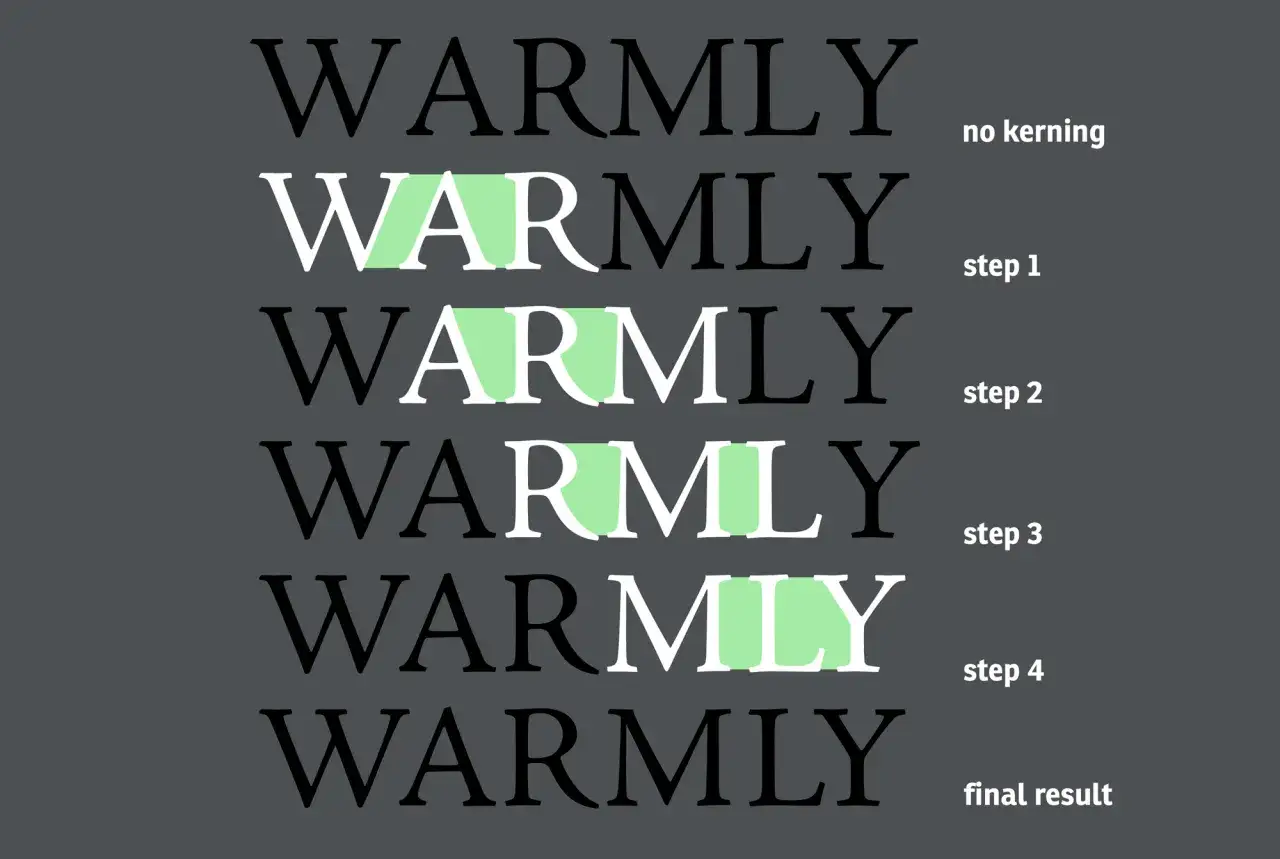
Jak ocenić efekt w druku i na ekranie
Najpewniejszy test to wydruk próbny w skali 100 procent, najlepiej na papierze zbliżonym do finalnego. Na ekranie interfejs często wybacza zbyt ciasny lub zbyt luźny rytm, ale papier pokazuje go bez litości, zwłaszcza przy ciemnych tłach i grubych krojach. Przy projektach związanych z fotografią i drukiem to szczególnie ważne, bo napis i obraz muszą grać razem, a nie konkurować o uwagę.
Ja traktuję ten etap jak ostatni, ale bardzo ważny przegląd przed publikacją albo drukiem. Gdy litery trzymają równy rytm, napis staje się pewniejszy, a cała kompozycja nabiera klasy bez zbędnego wysiłku. Właśnie dlatego ta drobna korekta tak dobrze sprawdza się w materiałach, gdzie obraz, tekst i jakość wykonania muszą tworzyć jedną całość.